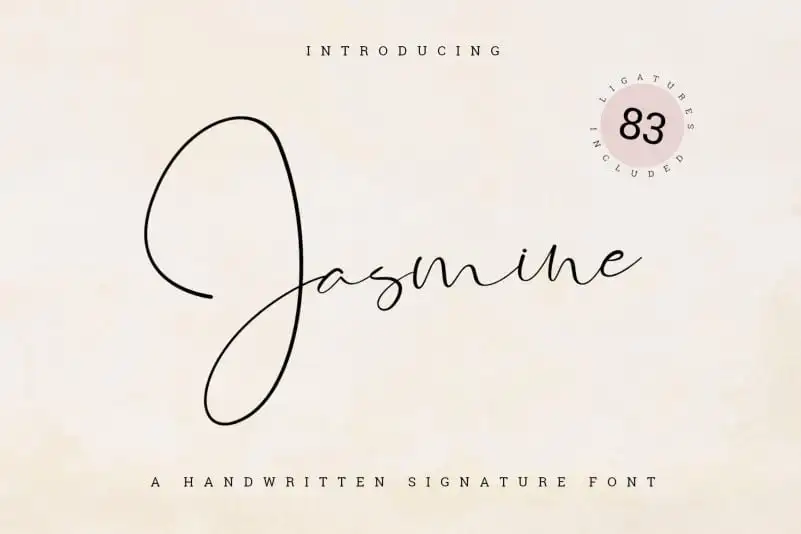
Jasmine Signature Font – Fonte Grátis
Jasmine Signature Font
A Jasmine Signature Font é uma deliciosa mistura de letras manuscritas criada por Jimtypestudio, especialmente pensada para entregar uma experiência visual suave e natural que se assemelha a um autêntico selo de firma. Este recurso gráfico excede com elegância no design de marca, arte fotográfica, convites, frases motivacionais, watermarking, anúncios, criação de produtos, etiquetas e muito mais. Seu aspecto autêntico é resultado de uma vasta gama de 83 ligaturas incorporadas, além da composição única de caracteres padrão Jasmine. Este design handwritten carrega um toque único que faz dele uma escolha perfeita para quem deseja dar um visual atraente e personalizado à sua próxima criação gráfica.